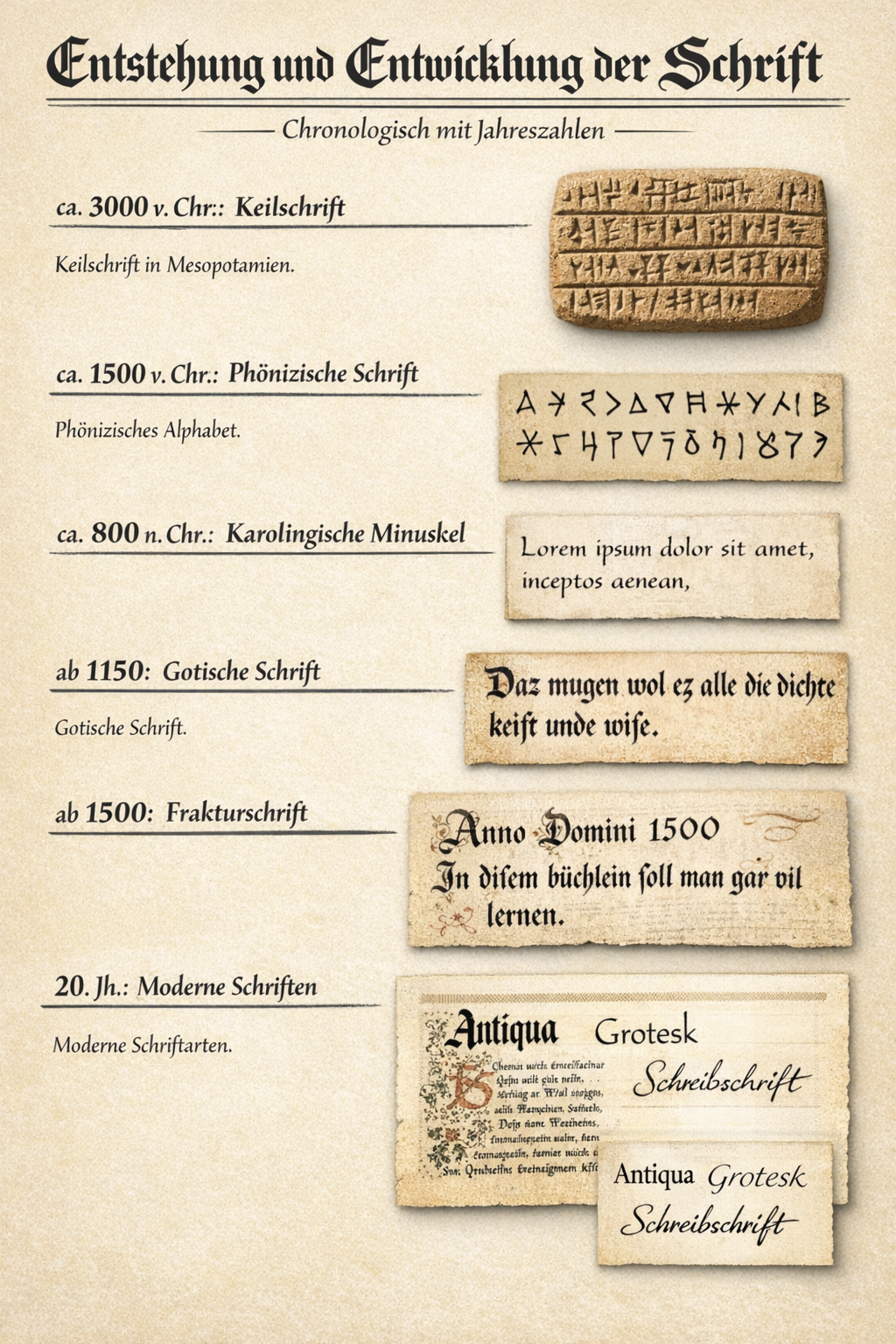
Die Schrift beginnt mit einfachen Bildzeichen, entwickelt sich über Silben- und Lautzeichen zu komplexen Schriftsystemen — und am Ende steht das Alphabet, mit dem wir bis heute schreiben. Die folgende Übersicht zeigt diesen Weg im Diagramm, mit Stationen, die jeweils auf eine eigene Detailseite führen.
Von den Anfängen als Sammlung von Piktogrammen über die Silbenschrift bis zur ersten reinen Alphabetschrift — ein Bogen, der mehrere Jahrtausende umspannt und am Ende in unserem heutigen Alphabet mündet.